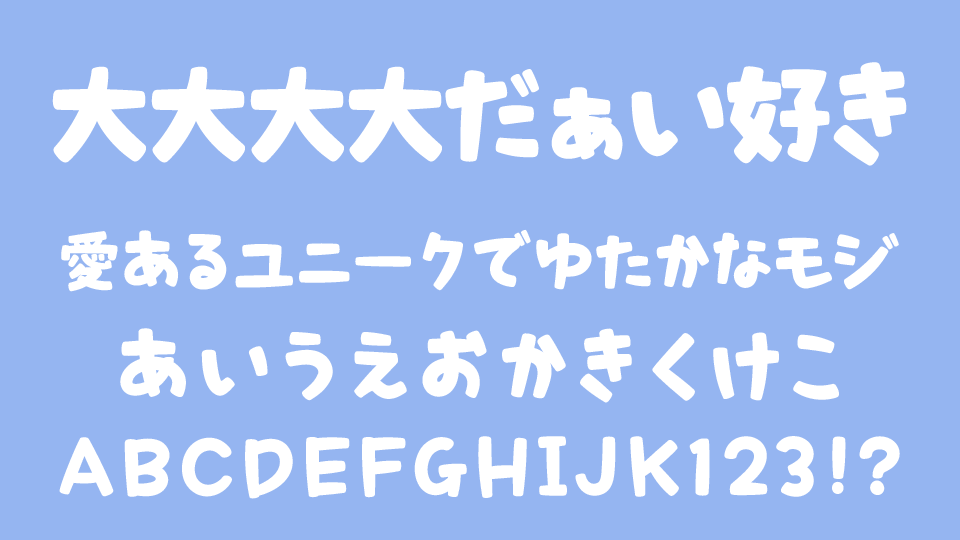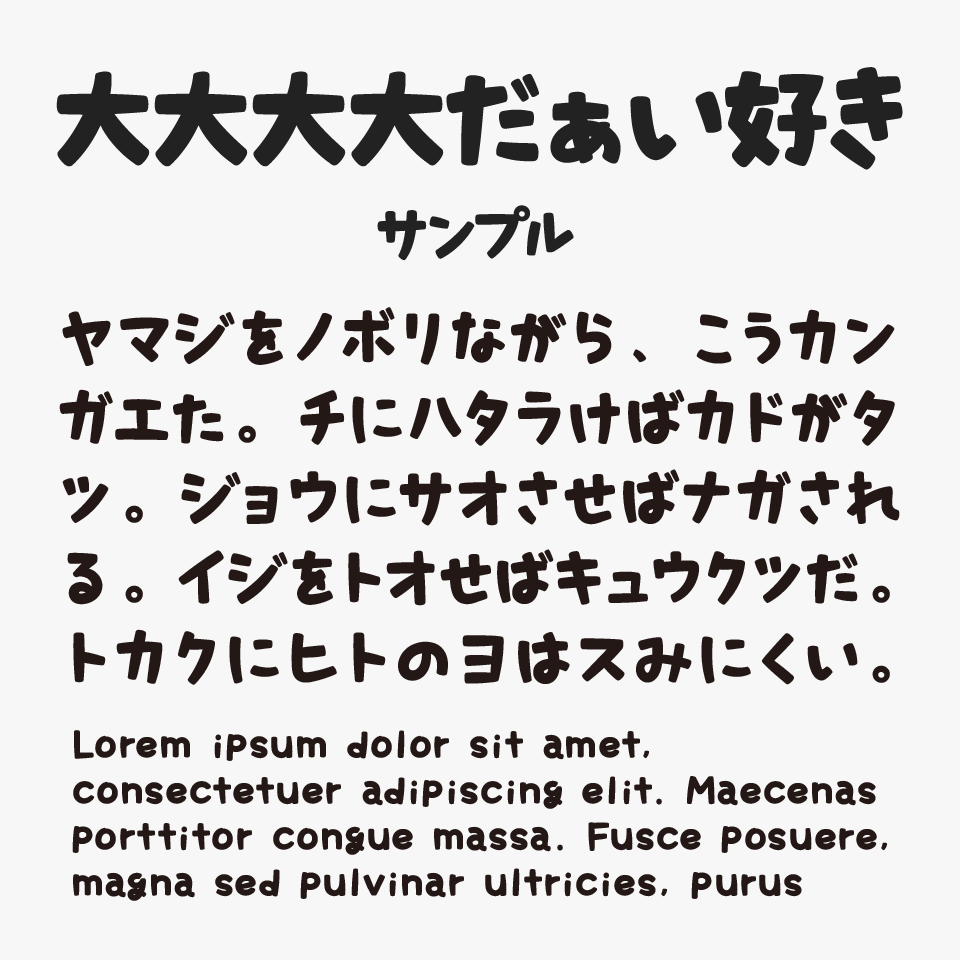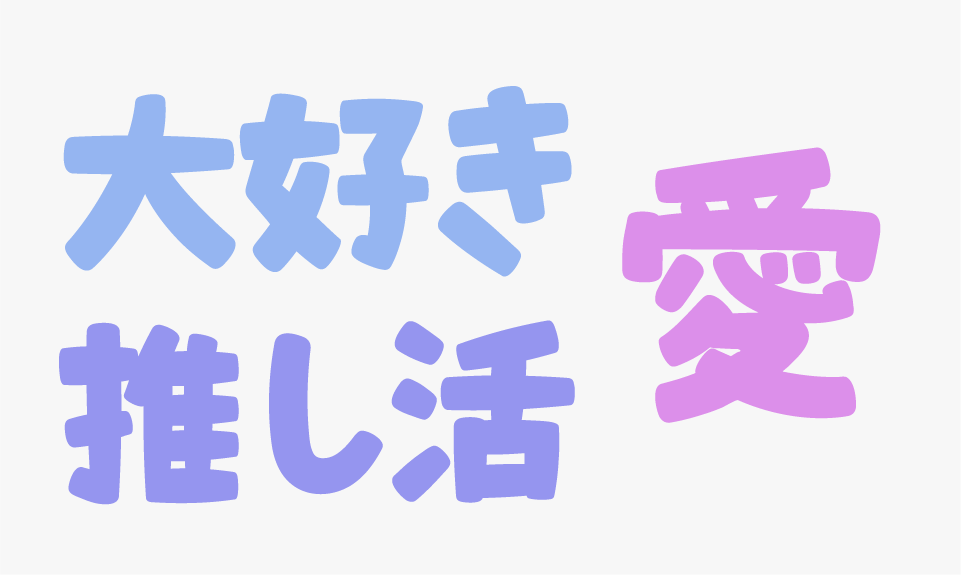
大大大大だぁい好き
大大大大だぁい好きフォントは、手書きの勢いとゆるさをそのまま活かした、賑やかで元気いっぱいの可愛いデザインフォントです。
線の太さが均一でなく、筆圧の強弱がそのまま字形に反映されており、描いた人の感情が滲み出るような温かみのある文字となっているので、推し活などにもぴったりなフォントです。
漢字収録は有料版のみですが、推し活グッズや応援うちわなどにもぴったりな可愛らしいフォントとなっています。